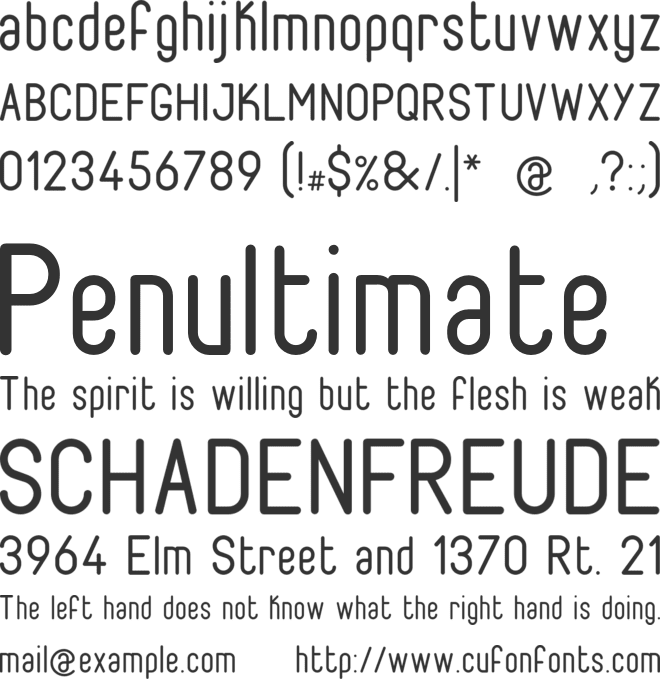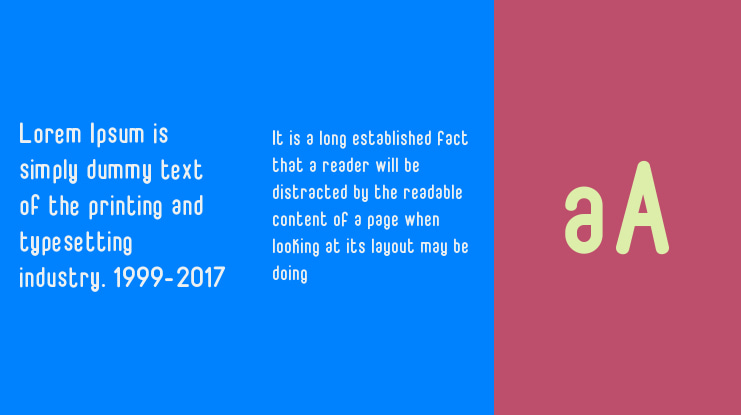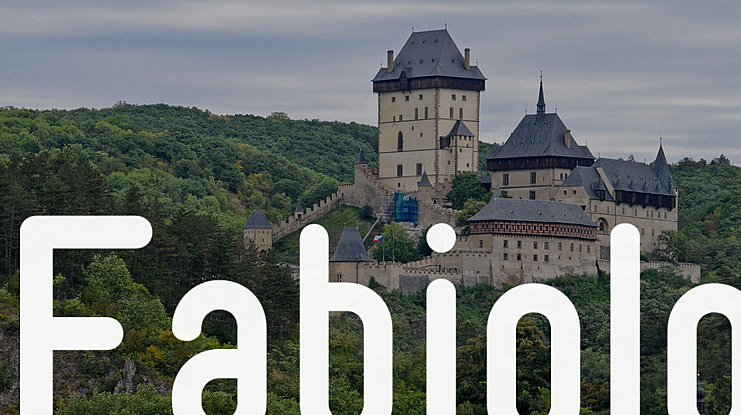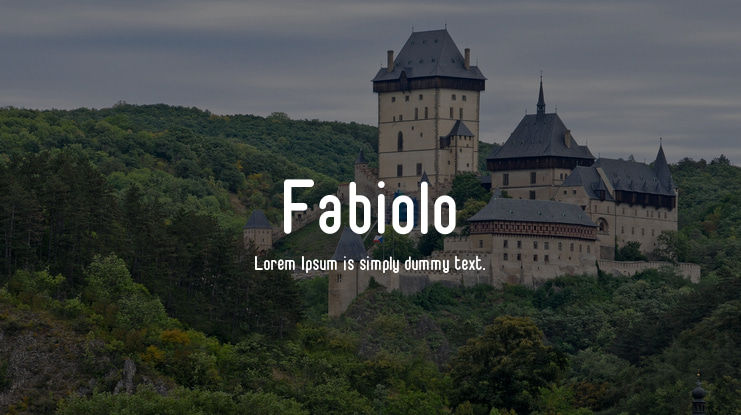
Fabiolo Font Family
Je cherche à concevoir une typo suffisamment sobre pour être utilisée dans un large spectre de graphisme différents tout en gardant une personnalité élégante et discrète. Voici donc ma première fonte maison.